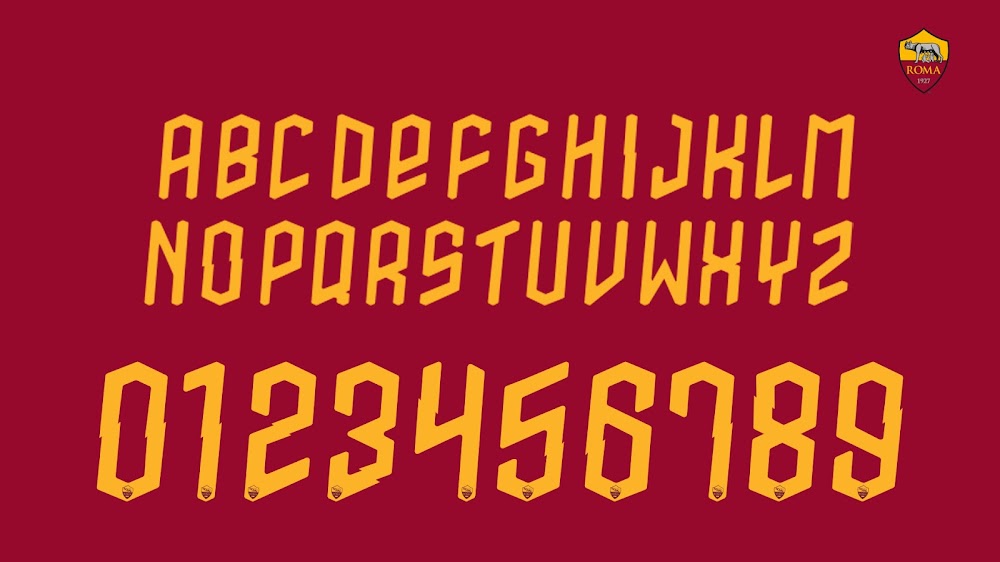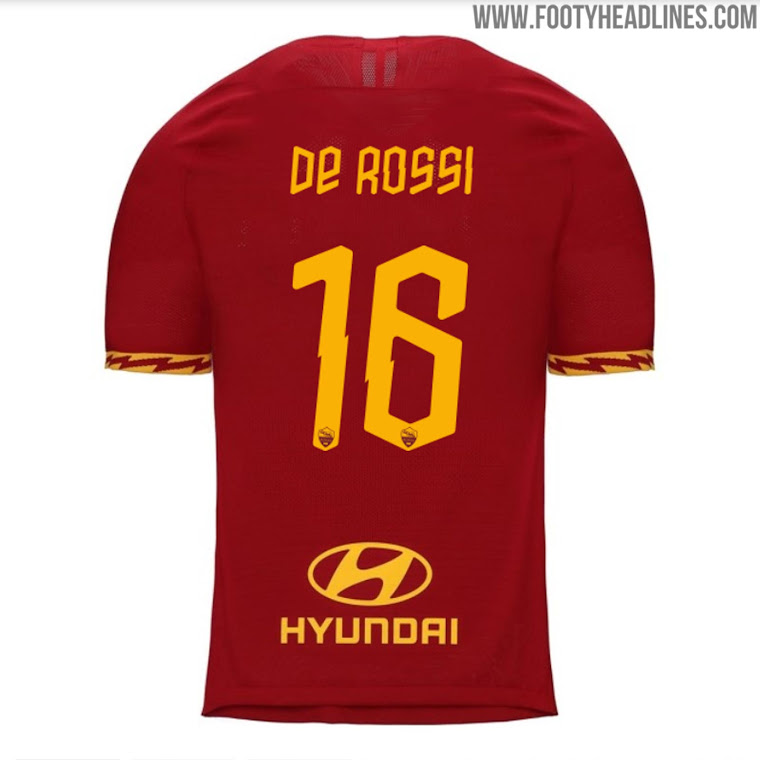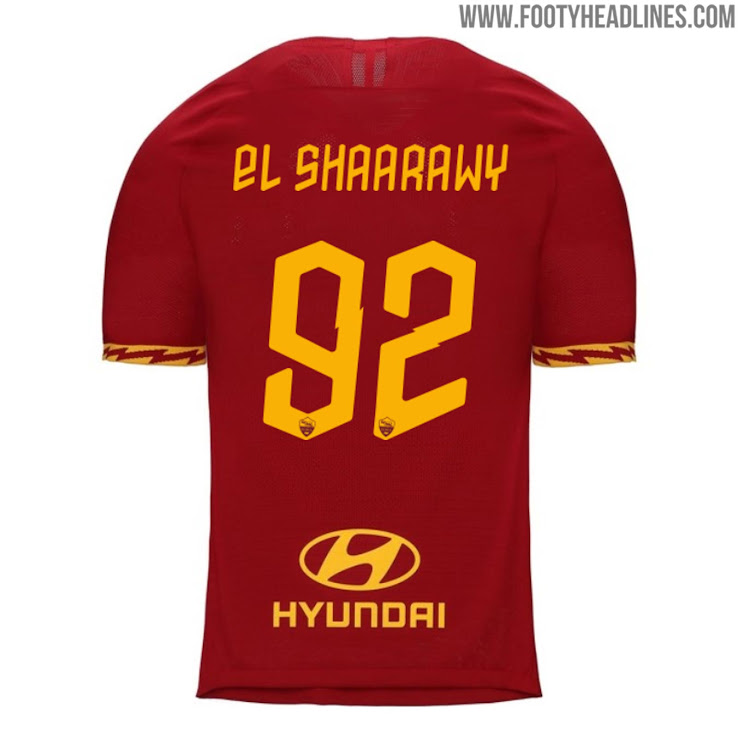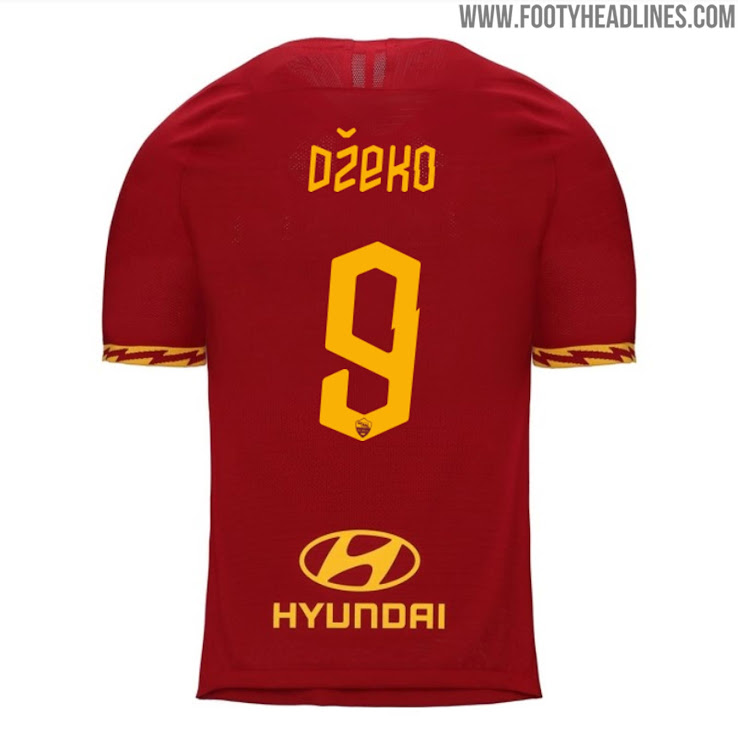
Verrückte Nike AS Rom 19-20 Trikot-Schriftart enthüllt
Das neue Nike AS Rom 2019-20 Trikot wurde am Donnerstag vorgestellt. Mit der Präsentation des neuen Trikots brachte der Klub auch eine brandneue Schriftart für die Saison 2019/20 heraus, die vom Trikot-Design inspiriert wurde.
Die Roma wird das neue Heimtrikot am Sonntag gegen Parma debütieren - es wird das letzte Spiel des legendären Roma-Spielers De Rossi sein.
Die neue Nike AS Rom 19-20 Trikot-Schriftart hat ein einzigartiges Design, das vom Blitz-Druck des Trikots inspiriert ist und sich durch ein außergewöhnliches, sehr kraftvolles Aussehen auszeichnet.
„Römische Mythologie und ihr Einfluss auf Römische Identität spielte eine große Rolle bei diesem Konzept. Dieses Jahr war Jupiter unser Fokus und der Blitzschlag war ein offensichtliches und ausdrucksstarkes Symbol,“ erklärt Pete Hoppins, Nike Football Apparel Senior Design Director.